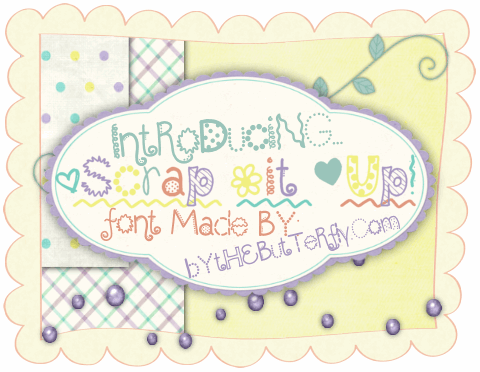
A ScrapItUp é uma fonte script de Hamilton que oferece flexibilidade para criar designs imersivos e envolventes no seu projeto. Se você está procurando por uma fonte que permita sobrescimas sublinhadas sutis, a cada dois ou três letras, nada melhor do que ScrapItUp. Suas linhas elegantes e fluidas permitem um estilo de escrita agradável que se adequa perfeitamente para criações digitais modernas. Os pontos finos e detalhes precisos da fonte garantem que qualquer texto impresso com ela seja elegante, particularmente quando combinado com seus desenhos suaves e sutis. Uma das características mais interessantes desta fonte é a sua capacidade de gerar sobrescimas suaves após cada dois ou três letras. Para isso, basta pressionar o _ (underline) no teclado. Esse recurso torna ScrapItUp uma escolha versátil e conveniente para designers gráficos que valorizam a personalização em seus projetos. Essas características, aliadas ao seu estilo moderno e fluido, fazem da ScrapItUp uma opção perfeita para trabalhos digitais variados, desde design de logos até criação de fontes personalizadas.